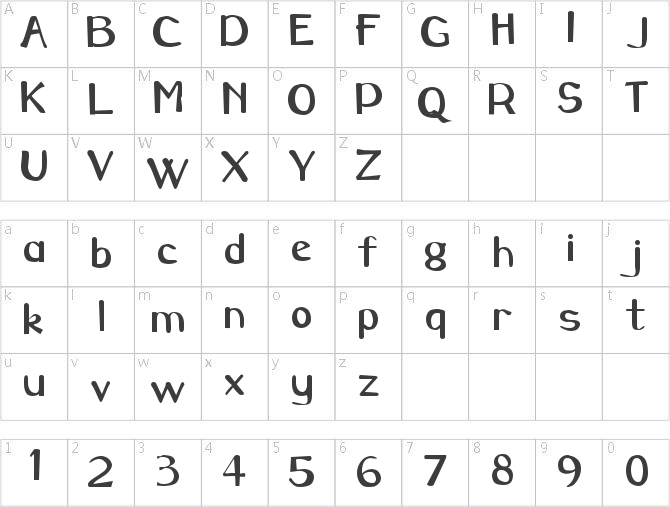
字體名稱: Caraway
CarawayBold
CarawayBold介紹
CarawayBold字體字庫是一款讓人賞心悅目、百看不厭的英文字體,適合各類廣告和產(chǎn)品包裝設(shè)計(jì)應(yīng)用,字體大小0.03MB,格式為ttf字體,上傳用戶是哼哼哈兮,作者/版權(quán)方為未知
CarawayBold效果圖